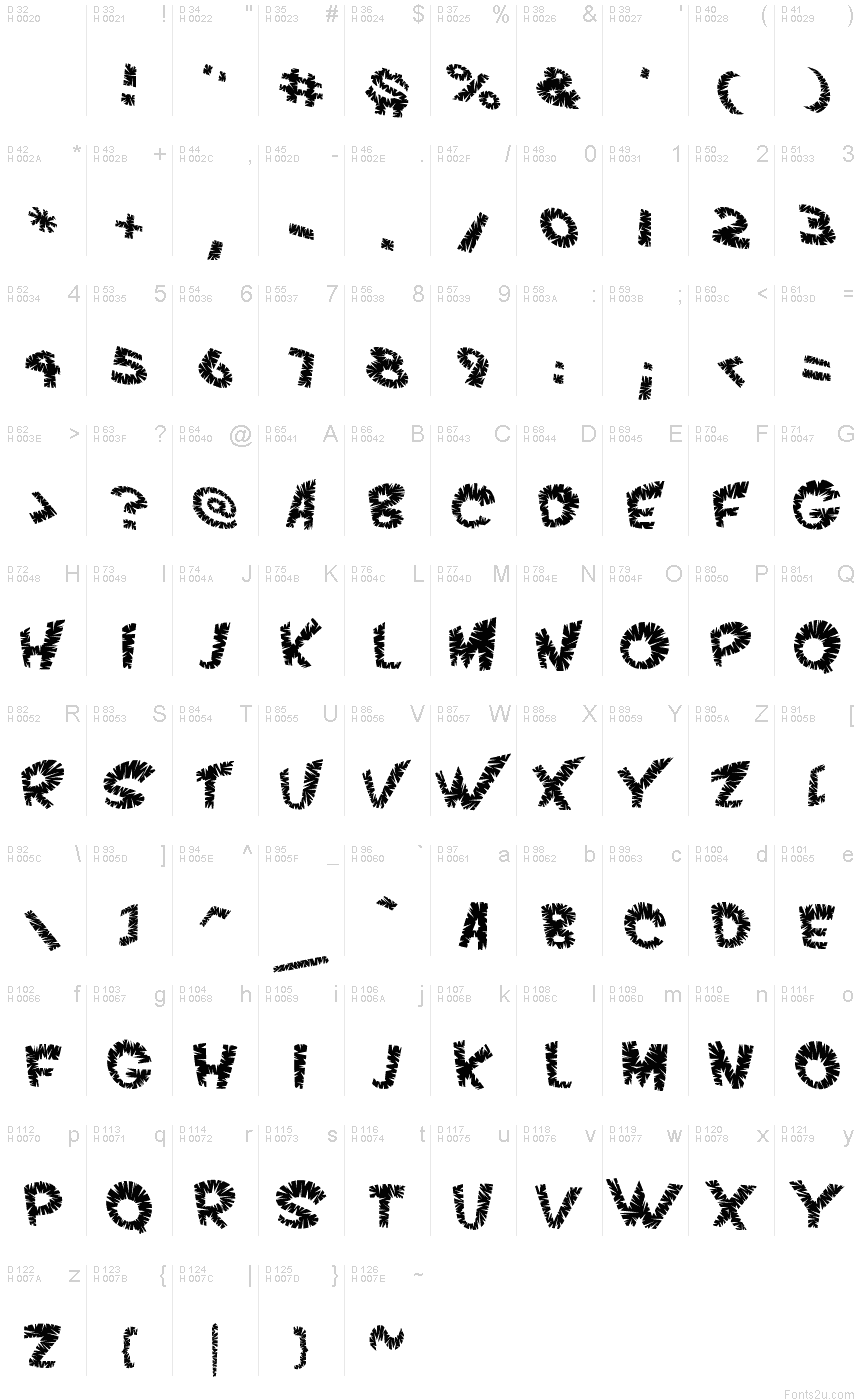
VTC Scream It Loud Sliced to darmowy krój pisma w stylu „cut-up” od V.T.C. Vigilante Typeface Corporation, emanujący frenetyczną energią listu z żądaniem okupu, żywcem wyjętym z kultury zinów lat 90. Litery są zbudowane z poszarpanych odłamków, więc nawet zaokrąglone formy wyglądają na posiekane, chaotyczne i lekko niestabilne, a nie wygładzone czy zabawne.
Dzięki temu ten darmowy font jest naturalnym wyborem na punkowe ulotki, plakaty do horrorów i komedii, okładki mixtape'ów, nagłówki undergroundowych magazynów oraz karty tytułowe, które potrzebują dynamiki bez użycia animacji. Sprawdza się najlepiej w krótkich fragmentach, gdzie posiekana sylwetka liter mówi sama za siebie – zwłaszcza w głośnych nagłówkach i napisach w stylu logo, które mają sprawiać wrażenie improwizowanych, surowych i wykonanych ręcznie.